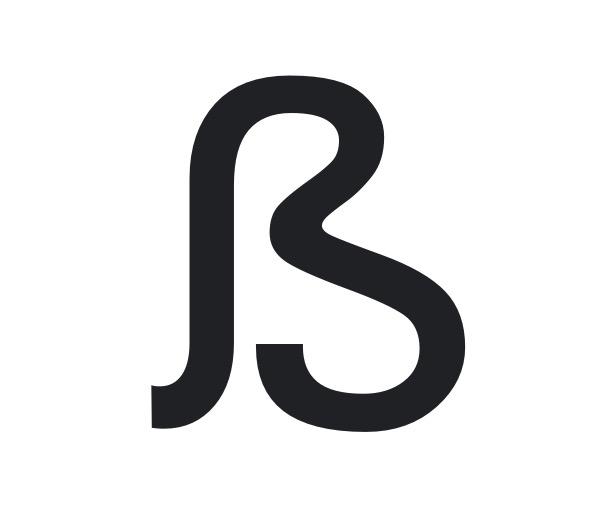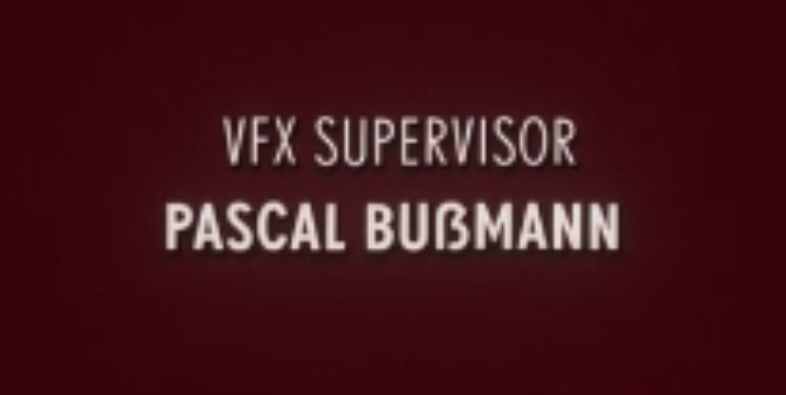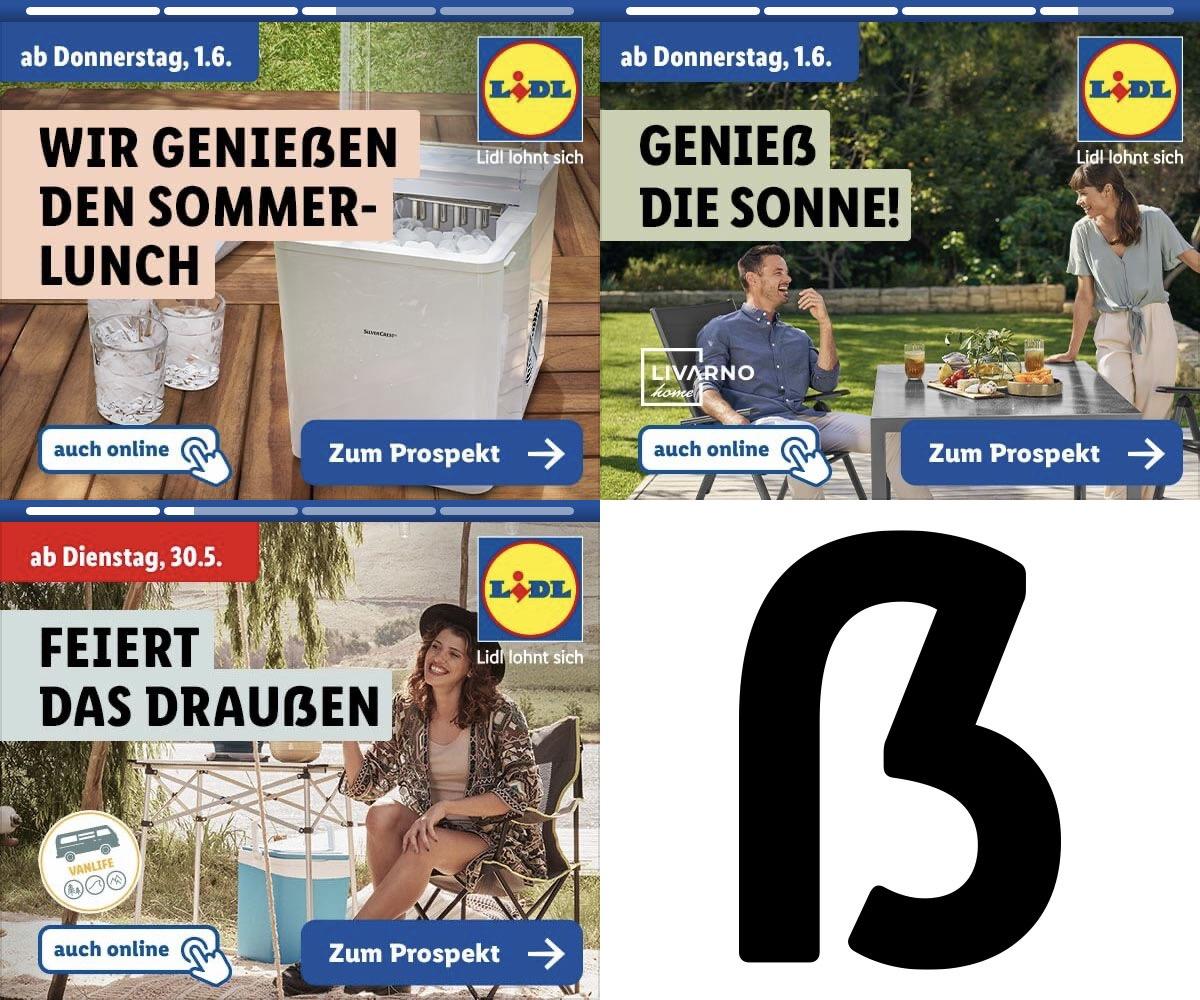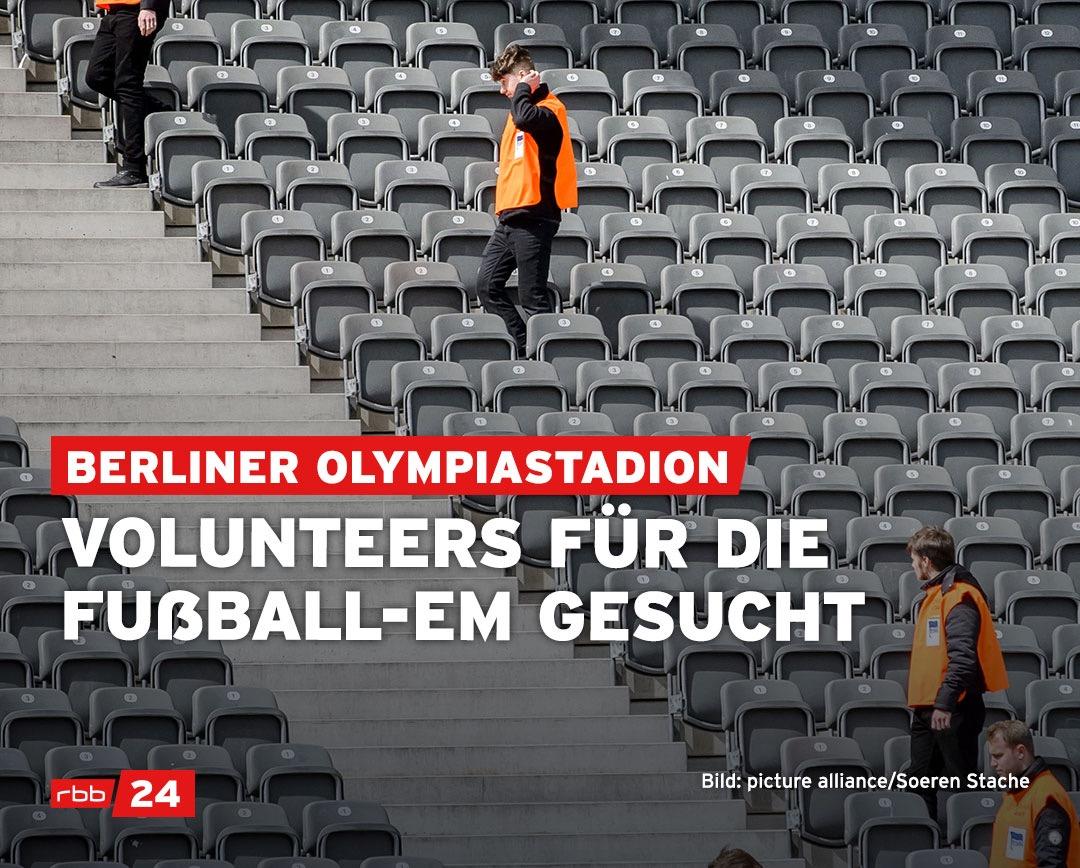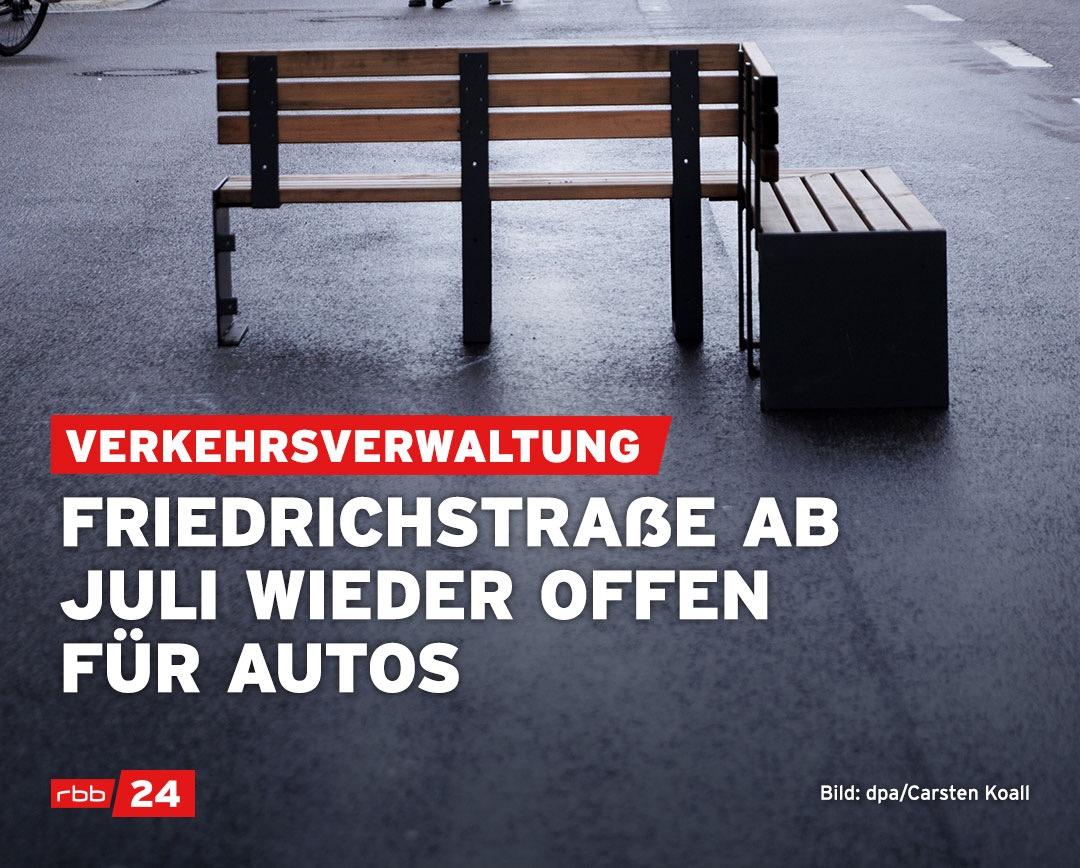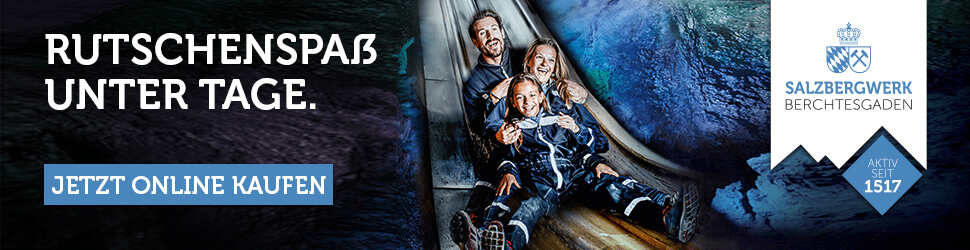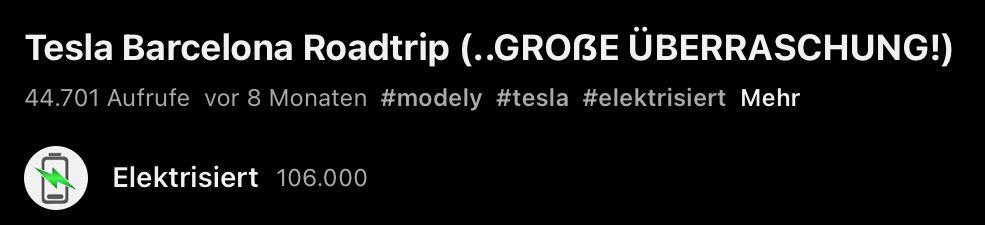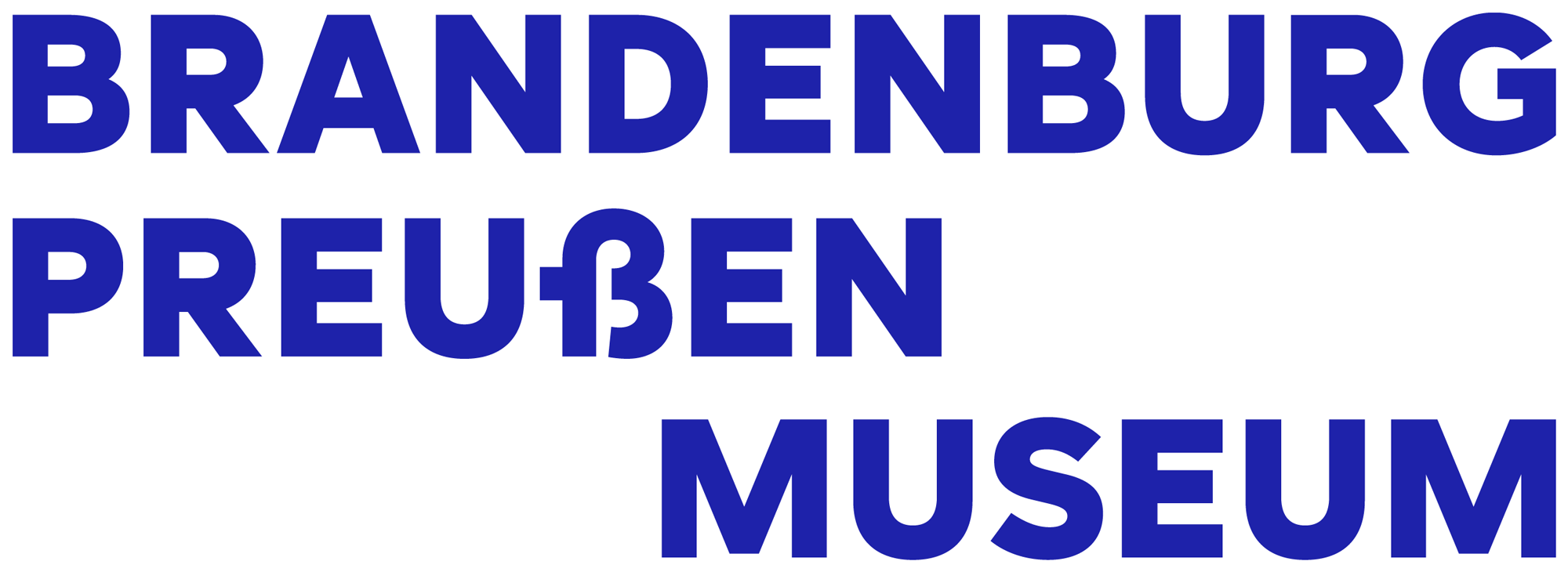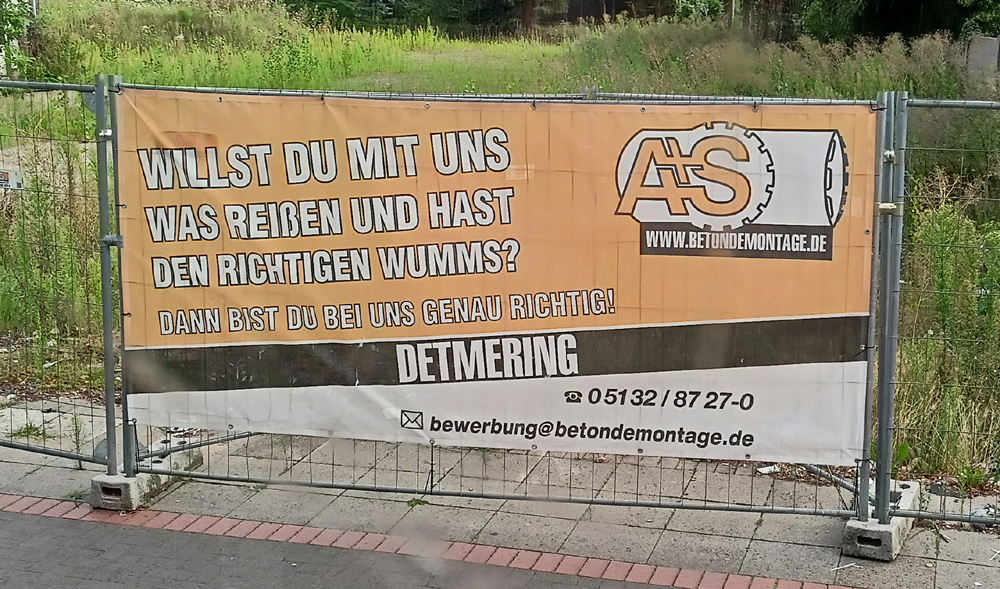
ist das nun ein misslungenes Gemein-ß oder ein falsch eingesetztes Versal-ẞ?
Da müsste man mal in die Schriftdatei schauen können. Auf jeden Fall leider daneben.
Aus dem Abspann der großartigen Serie Kleo (schrottige Auflösung ist dem Internet geschuldet, ich vermute, dass es in 4k, oder was auch immer Netflix als bestes bietet, gestochen scharf ist):image.png.ef28d09db2300bb4f3cf349db7c44cc2.png
Roboto war schon immer gut für »Überraschungen«, wie wir hier schmunzelnd feststellen können: https://typographica.org/on-typography/roboto-typeface-is-a-four-headed-frankenstein/ Damals wurde, wg. der fundierten Kritik, die Schrift überarbeitet. Jetzt sieht sie zwar etwas weniger aus wie ein Patchwork von Alles-was-irgendwie-hip-ist, aber mit dem neuen Versal-ẞ hat Google sich um etwa 10 Jahre in ihre eigene Schriftgeschichte zurück katapultiert. Anscheinend hat Google nicht viel aus ihre Roboto-Geschichte gelernt.
Voriges Jahr kam mir das Buch »400 Eszett-Schnitte« unter Augen. Eine erstaunliche Sammlung … nicht nur weil einige Designer es offensichtlich nicht geschafft haben, ein brauchbares, zur eigenen Schrift passendes »ß« zu gestalten, aber auch weil viele Zeichen (egal ob Gemein-ß oder Versal-ẞ) Beulen und Kicken aufweisen. Beschäftigt so mancher »Google-Designer« sich eher mit »Slot-Filling« und weniger mit Gestaltung?
Das war auch mein erster Gedanke – wenn einmal der Wurm drin ist …
Von denen gibt es neben dem ẞ bei der Flex leider auch noch viele weitere. Zumindest wenn man beim Typetester mal die Extreme der Regler ausprobiert, gibt es ästhetisch sehr unschöne Beulen und Überlagerungen. Das kann man eigentlich auch nicht mehr mit dem Hipster-Ansatz rechtfertigen. Und es verblüfft besonders wenn dieses Mal sogar Leute der namenhaften Foundry  Font Bureau beteiligt waren. Wahrscheinlich war es bei der Anzahl der Variable-Font-Achsen schier unmöglich das auch noch stimmig und vollständig auf gegenseitige Abhängigkeiten zu programmieren. Nur so kann ich mir das gerade erklären. Oder der Typetester bei Google-Fonts wirft fehlerhafte Ergebnisse aus. Kann ich mir aber nur schwer vorstellen.
Ich würde sagen, das Versaleszett IST der Wurm … :-|
Erinnert mich spontan an eines dieser garstig verbogenen Sitzmöbel (aka „Skulpturale Sessel“), das mir bei meiner Recherche gerade untergekommen ist … ;-)
Das große Eszett, demnächst auf 2-Euro-Münze:
AAAAAAH! KARL DER GROBE! 😲
Scheint aber korrigiert worden zu sein(?):
Nachtrag: Die Münze kann man jetzt (bzw. seit März) bei Filialen der Bundesbank oder auch bei Filialen verschiedener Banken erhalten. Und das Versaleszett ist zum Glück nicht so ausgefallen, wie auf der oben zu sehenden Visualisierung. Auf Wikipedia gibt es ein Foto der realen Münze:
Gerade auf der CNN-Website gesehen:
Nicht schlecht, aber zu komprimiert. Man vergleiche mit dem U…
(Museo?)
Hmm.
Dabei hat die verwendete Schrift (Candor) sogar ein Versaleszett an Bord. Oder übersehe ich da eine konzeptionelle Entscheidung?
Ganz anständig; vielleicht innen etwas gedrängt?
Ja, finde ich auch. Aber das ist ja unterm Strich der oben komplett runden Form geschuldet. Breiter fände ich dann auch schon wieder schwierig. Ein weiterer Grund es oben wenigstens zu einer Seite gerade zu formen. 😉
Ich fand es bemerkenswert wie Achim auf das Thema eingegangen ist. Und habt Ihr Euch mal die Kommentare durchgelesen? Da wird das ẞ inzwischen im Grunde bei allen als Standard vorausgesetzt. Beeindruckend. 🥰